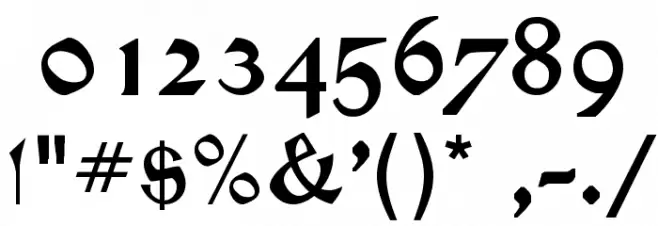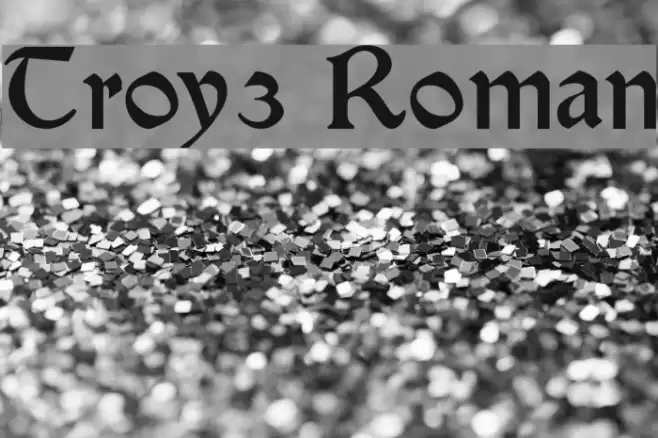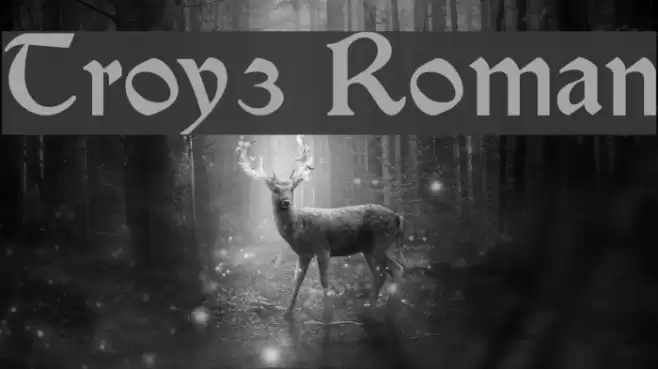
Troy3 Roman Font
| Nom | Troy3 Roman |
| Poids | Roman |
| Catégories | Gothic |
| Style général | Classic |
| Cas d'utilisation | Logos, Headlines, Certificates |
| Projets proposés | Suitable for historical documents, certificates, branding for luxury goods, or any project needing a traditional and elegant touch. |